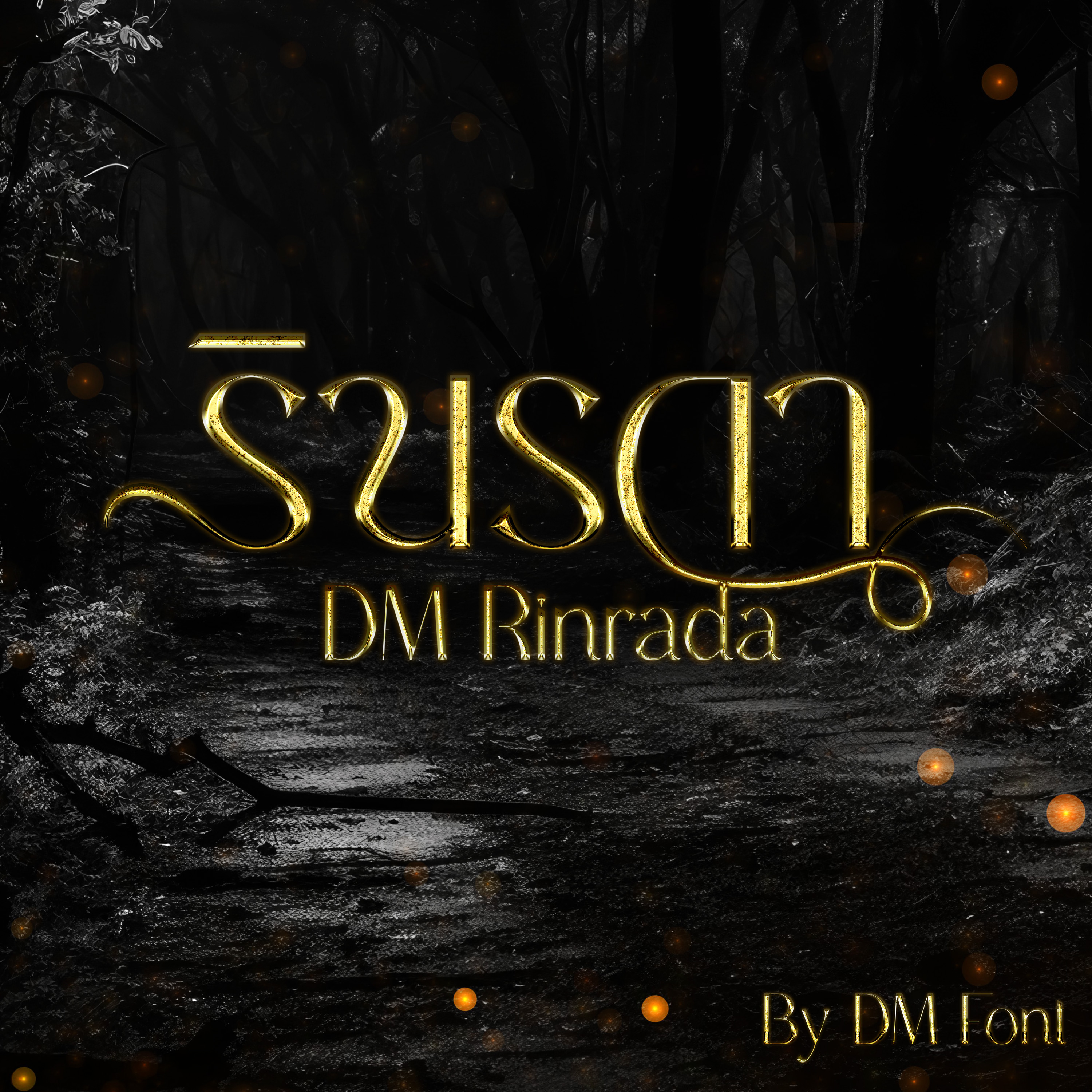
DM Rinrada (ดีเอ็ม รินรดา)\
ชื่อฟอนต์ : DM Rinrada (ดีเอ็ม รินรดา)
ฟอนต์ DM Rinrada (ดีเอ็ม รินรดา) เป็นฟอนต์แนว sans serif ที่ผสมผสานความแฟนตาซีเข้าไป เหมาะกับการนำไปทำเป็นพาดหัวหรือข้อความสั้นๆในโปสเตอร์ต่างๆ